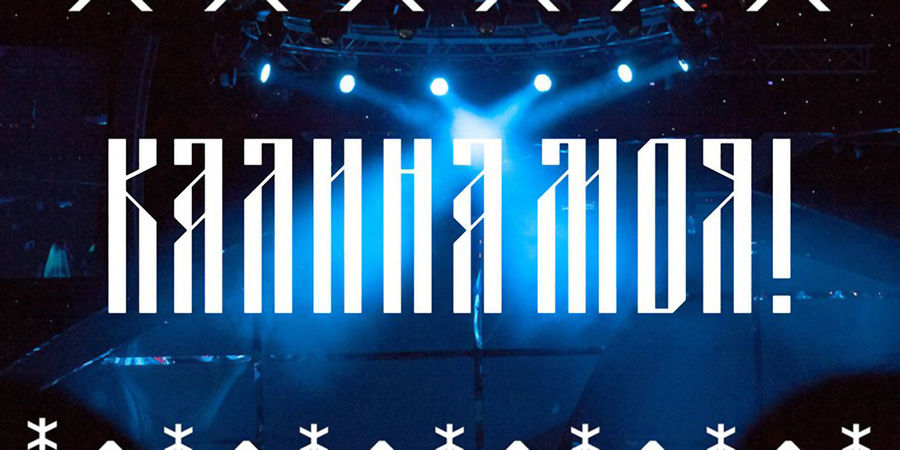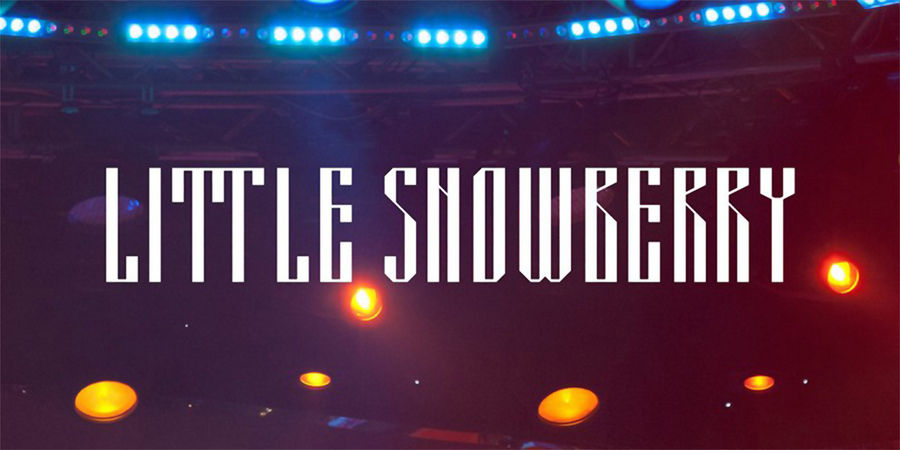
КалинкаМалинка – це сучасний технократичний шрифт, заснований на кириличній в'язі. Він підтримує багато мов, наприклад, іспанську, португальську, німецьку та французьку в латинській кодовій сторінці та українську, білоруську і російську у кириличній, і містить різні варіанти літер для створення цікавої та різноманітної літерації. КалинкаМалинка ідеальна для заголовків, назв та не підходить для великих обсягів тексту. Може використовуватися у плакатах, рекламі, вивісках та декоративних патернах. Шрифт розроблено Тетяною Ляшенко у 2015 році.
Асоціації з сімейством шрифтів KalinkaMalinkaОсобистість і характер гарнітури:
високий, стрункий, гострий, різкий, дзвінкий, музичний, незграбний, ламаний, холодний, модний, сучасний, характерний, оригінальний, самобутній, помітний, грайливий, яскравий, твердий, точний, рівний, архітектурний, дивний, іронічний, міський, свіжий, виразний, зимовий, крижаний, радісний, живий, екзотичний, психоделічний, нічний